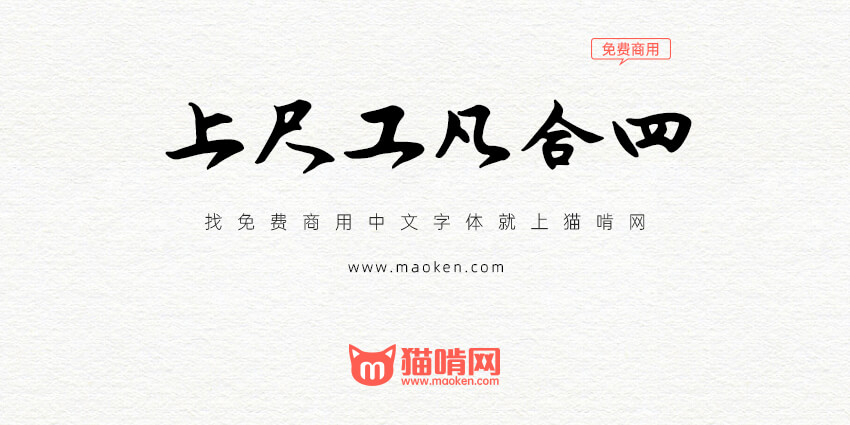
如今全国疫情仍然未敢放松,我们工作室的许多客户,都喜欢在家抄工尺谱,一边抄,一边熟悉乐曲。
不过,独乐乐不如众乐乐,传统的线下抄谱,既不利于长久保藏,也不方便随手使用,也不方便网上互相分析传播。而且,抄坏了还没法改,真的是效率很低哦!因此,数字化的抄谱,不但可以永久保存,还可以每个人都抄得很美观,书法不好,也没关系,只要有好的字体,抄出来照样唯美,而且还可以随时修改,并且好的谱子,还可以彼此分享,一页谱子,还能随时拿出来对着手机唱,实在是演员和曲友居家必备之物。
为了传播昆曲、也方便大家大家数字化抄谱,女神节之际,我们工作室推出了这款免费字体,当前1.0版本。
佳节之际,润植家艺术工作室又上免费公益礼品来了!全世界首个:昆曲专用工尺谱输入免费公益字体——润植家工尺谱字体,不但可以个人使用,还可免费商用哦!